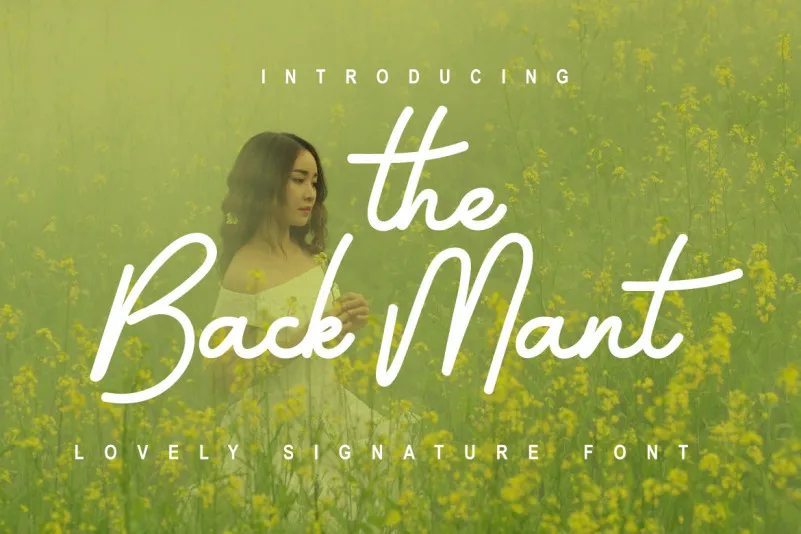
The Back Mant Font – Fonte Grátis
The Back Mant Font
Esta é uma fonte de letra cursiva que traz consigo um toque leve e fluido. É perfeita para aqueles projetos de design que buscam dar um brilho sofisticado, sem ser excessivamente pesado ou chamativo. As letras deste script deslizam delicadamente ao longo da linha base, criando um efeito elegante em qualquer projeto que você desejar criar. A fonte “The Back Mant” de Makaryo é uma excelente escolha para quem busca dar brilho às suas criações gráficas, seja em impressões digitais ou físicas, mantendo um equilíbrio entre sofisticação e simplicidade.